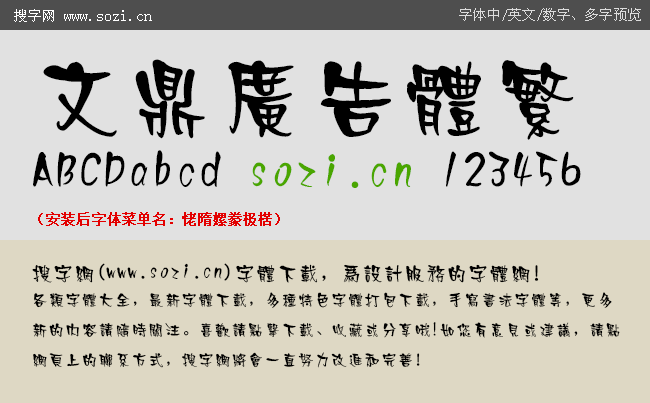
文鼎廣告體繁
文鼎廣告繁體是搜字網(wǎng)提供一款免費(fèi)中文字體下載。文鼎廣告體分為簡(jiǎn)體字體和繁體字體,此為繁體。文鼎廣告繁體字體為專(zhuān)用廣告字體,其字形大膽形象,可用于各種廣告設(shè)計(jì)。是字型專(zhuān)業(yè)領(lǐng)導(dǎo)廠(chǎng)商-文鼎科技作品。